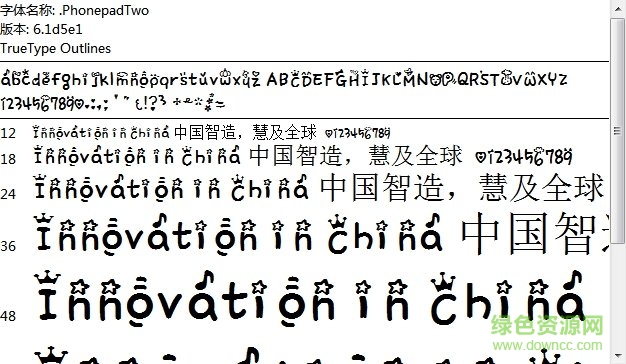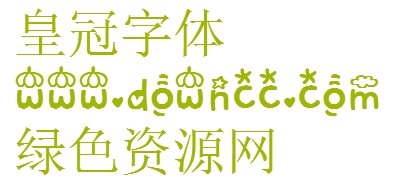
小皇冠字體ttf
皇冠字體是一款有著可愛皇冠圖案的卡通字體,讓文字有著尊貴的裝飾品,彰顯貴族風(fēng)范,是一個(gè)非常特色鮮明的pop字體,快來綠色資源網(wǎng)收藏吧!
小皇冠字體ttf介紹
皇冠字體上不僅有著可愛的小皇冠圖案,還有音符、五角星和愛心符號等,讓文字更加美膩清新,給人十分搶眼的視覺呈現(xiàn),綠色資源網(wǎng)誠意推薦!
皇冠字體
皇冠字體包含三款字體,支持中英文、線體和標(biāo)準(zhǔn)體,繁簡文字均可使用,字體安裝完成后,在系統(tǒng)顯示phonepadtwo名稱,使用時(shí)請注意調(diào)試。